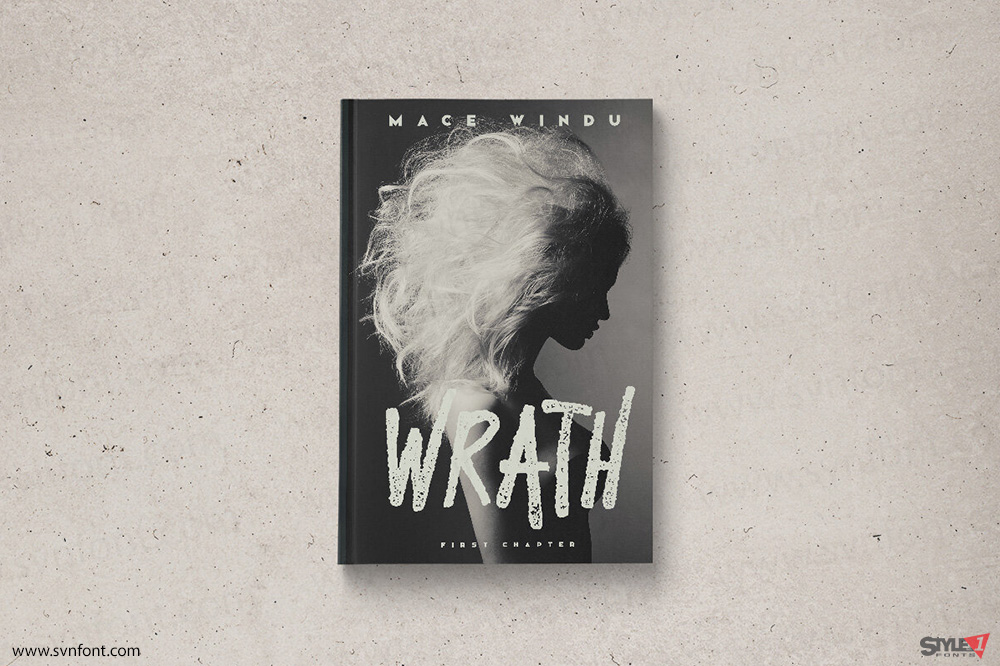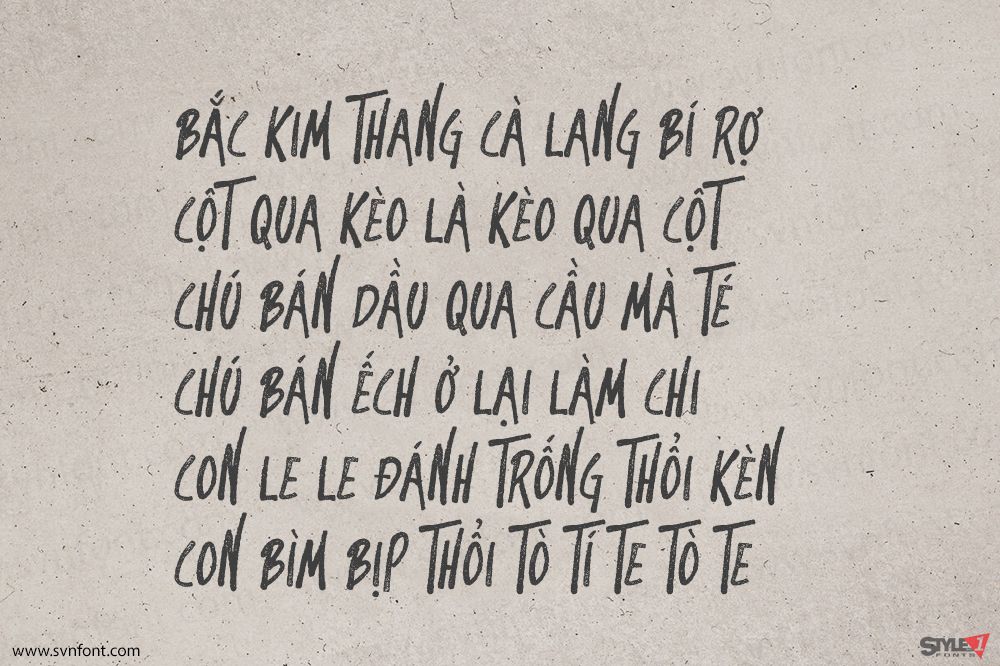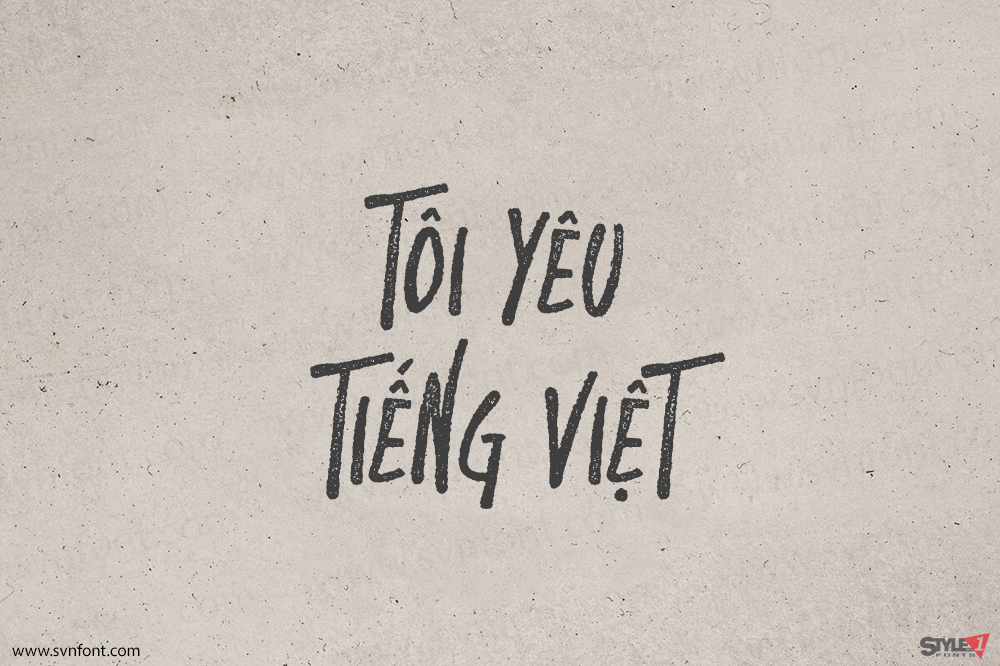
Brink là một phông chữ viết tay thô ráp với các chữ cái thay thế có thể bật tắt bằng phím Caps Lock. Nó bao gồm các chữ cái viết hoa đa ngôn ngữ, chữ số và dấu chấm câu.
Nhà thiết kế: Mehmet Reha Tugcu
Nhà phát hành: Tugcu Design Co.